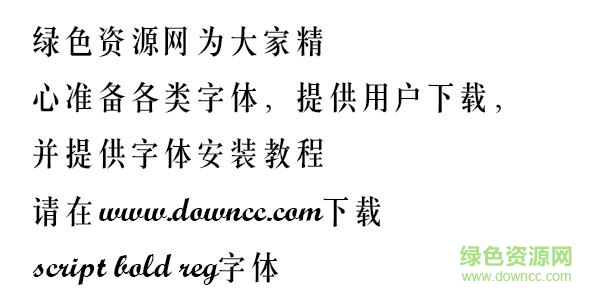
script bold reg英文字體ttf將帶給你濃烈的視覺效果,這款字體在用戶進(jìn)行網(wǎng)絡(luò)文字編輯以及交流聊天過(guò)程中都擁有著十分不錯(cuò)的顯示效果,如果運(yùn)用到媒體制作中將更加的增添光彩!
script bold reg字體ttf是一款不錯(cuò)的英文字體樣式,受到眾多用戶的喜愛,在使用的過(guò)程中即可以進(jìn)行各類效果添加也可以進(jìn)行文字編輯保存!